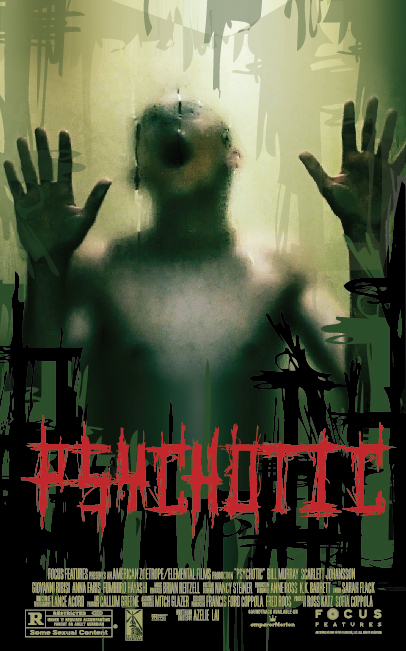
Psychotic to darmowy krój pisma w klimacie horroru, wyglądający jak napisy wydrapane na stronie suchymi, łamiącymi się pociągnięciami. Litery sprawiają wrażenie surowych i niestabilnych, z poszarpanymi poprzeczkami, długimi, igłowymi wyciągnięciami i ręcznie wykonanym rytmem, który bardziej kojarzy się z plakatami do horrorów typu slasher niż z wygładzonym gotykiem.
Ten darmowy font sprawdza się wszędzie tam, gdzie tytuł ma szybko wywołać niepokój – na plakatach horrorów, ulotkach na mroczne imprezy, demówkach metalowych, opakowaniach na Halloween czy w tytułach gier niezależnych. Działa również w przypadku krótkich haseł i logotypów, ponieważ surowe cięcia i wydłużone kolce budują klimat, zanim jeszcze zdążysz przeczytać tekst.
To krój pisma, który stworzyłem w ramach zadania na zajęcia z projektowania graficznego. Nie zawiera pełnego zestawu interpunkcji i znaków.